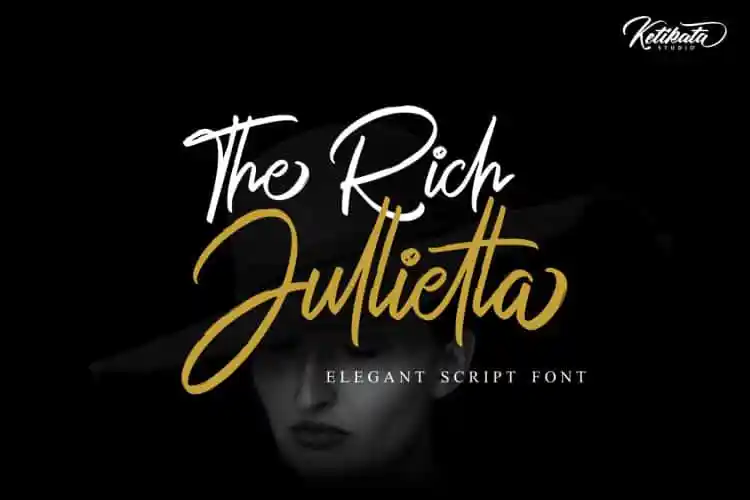
The Rich Jullietta Script Font – Fonte Grátis
The Rich Jullietta Script Font
Olá designer! Estou aqui para apresentar-lhe uma elegante fonte de script. Introduzimos The Rich Julietta Font ! Ela foi criada pela Ketikata Studio e tem um tom naturalmente rasgado, uma marca única que adicionará personalidade a qualquer projeto que você esteja trabalhando. A The Rich Julietta é perfeita para usar em diversos formatos de projetos, como convites de casamento, postagens nas redes sociais, materiais promocionais, citações, flyers ou embalagens e logotipos para marcação. Com um ar autêntico que não poderia ser mais original, esta fonte irá dar um toque especial ao seu projeto. É perfeito para aquelas ocasiões especiais como festas de casamento, ou mesmo para texturas simples em posts da sua página nas redes sociais, tornando-a uma ferramenta versátil que encaixa-se em vários campos de uso. Experimente a The Rich Julietta e veja como ela pode tornar seus designs mais únicos e distintos!